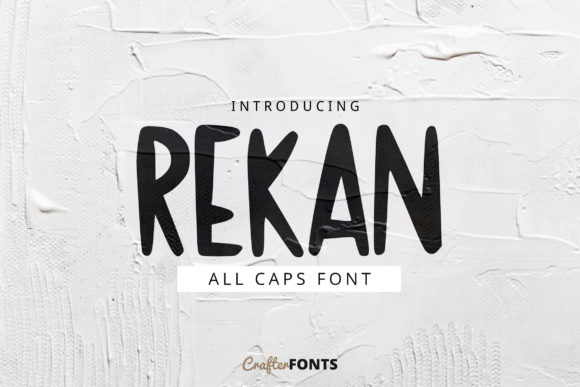
Rekan Display Font
Mencari elemen reka bentuk yang sesuai boleh menjadi mencabar, tetapi Rekan Display Font menawarkan koleksi luar biasa yang menaik taraf karya anda serta-merta.
Dicipta dengan ketepatan, Rekan Display Font menyediakan vektor yang bersih, tipografi yang licin dan lesen komersial untuk ketenangan fikiran.